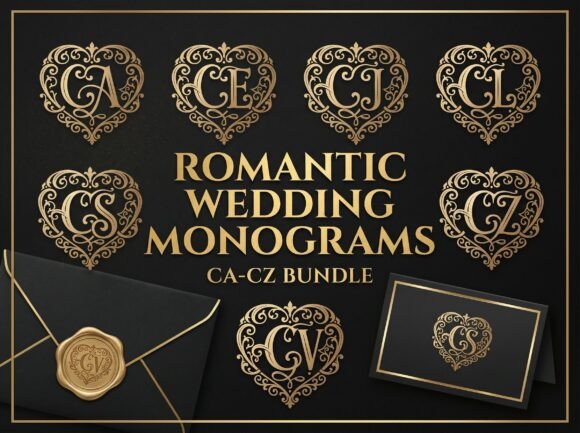
26 Romantic Wedding Monogram CA-CZ
หากคุณกำลังมองหาเนื้อหาคุณภาพสูงเช่น 26 Romantic Wedding Monogram CA-CZ แพ็คเกจพรีเมียมนี้เป็นตัวเลือกที่ยอดเยี่ยมสำหรับโปรเจ็กต์สร้างสรรค์ของคุณ
สร้างขึ้นอย่างแม่นยำ 26 Romantic Wedding Monogram CA-CZ ให้เวกเตอร์ที่สะอาด พิมพ์ตัวอักษรที่ราบรื่น และใบอนุญาตเชิงพาณิชย์เพื่อความสบายใจ
ไม่ว่าคุณจะสร้างผลิตภัณฑ์ POD (Print on Demand) คำเชิญงานแต่งงาน หรือกราฟิกโซเชียลมีเดีย 26 Romantic Wedding Monogram CA-CZ ก็เหมาะสมอย่างยิ่ง